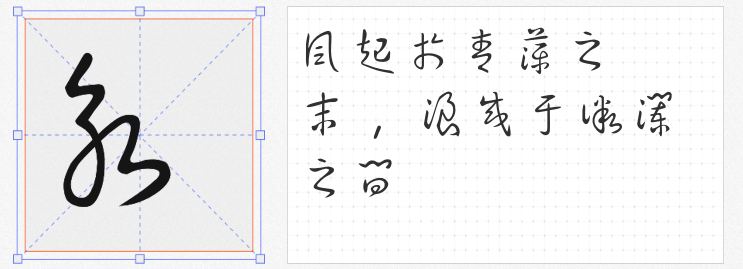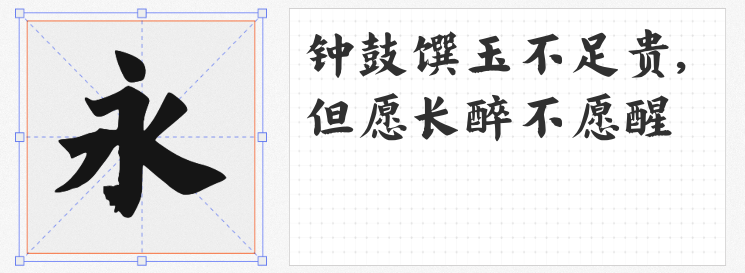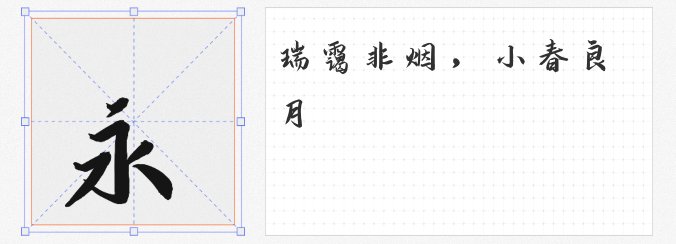
在数字化设计浪潮中,手写字体的独特韵味成为打破机械感的关键元素。本文精选四款免费可商用的手写字体,涵盖楷书、行楷、创意碑帖与狂草风格,助您在商业设计中传递东方美学的灵动与厚重。
1. 程荣光刻楷
作为一款以刀刻质感为特色的楷体,程荣光刻楷突破传统楷书的工整框架,在横竖撇捺间融入金属雕刻的硬朗线条。其字形结构严谨却不死板,转折处保留刀痕的毛边效果,既适合传统文化类海报的庄重表达,也能为现代科技产品的包装设计增添人文厚度。免费商用授权使其成为初创品牌打造文化底蕴的性价比之选。
2. 演示悠然小楷
这款融合行书笔意的小楷字体,通过均衡的笔画力度与克制的连笔设计,构建出"停而不断"的呼吸感。设计师巧妙保留手写时的自然抖动痕迹,让每个字符都像刚落笔的墨迹般鲜活。特别适用于茶饮品牌包装、古籍书封设计等场景,其略带拙朴的细节处理,恰与当下流行的"侘寂风"审美不谋而合。
3. 昆明海鸥体
作为全国首款融入红嘴鸥元素的创意字体,昆明海鸥体将鸟类飞行的动态曲线注入传统碑帖骨架。笔画起收处模仿鸥羽的轻盈弧度,中宫收紧的结构又延续了魏碑的稳重感。这款字体特别适合文旅项目、生态品牌视觉系统,其兼具现代简约与古典神韵的特质,能有效拉近与年轻消费群体的距离。
4. 草书 简入繁出
由贴吧大神mikhailcai耗时三年打造的狂草字库,完整收录17000余繁体汉字,覆盖从先秦典籍到现代文学的用字需求。字体以孙过庭《书谱》为蓝本,通过标准化处理平衡艺术性与实用性,既保留"笔走龙蛇"的视觉冲击力,又确保小字号下的可辨识度。非常适合文化展览主视觉、国风游戏UI等需要强烈情绪表达的场景。